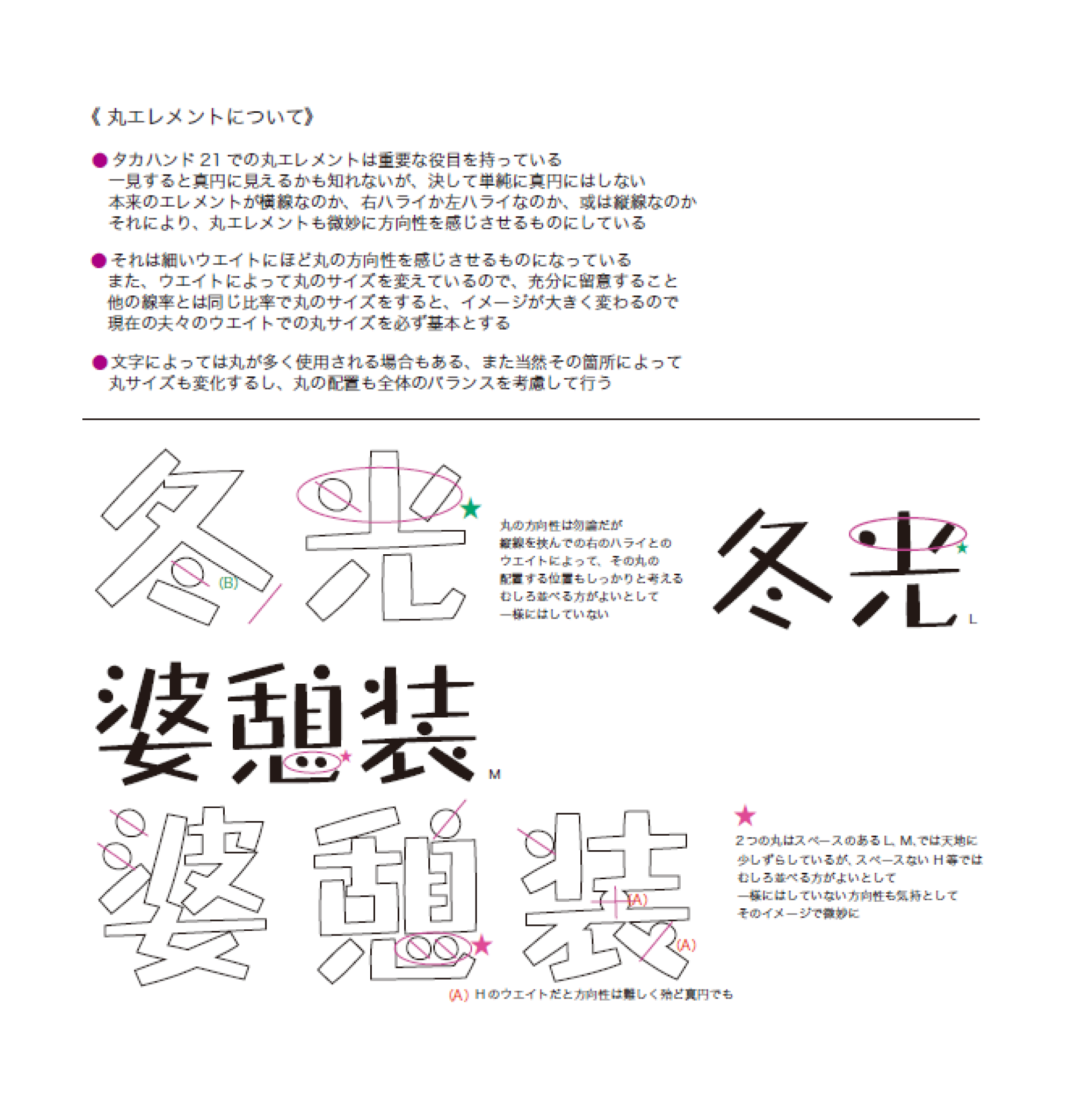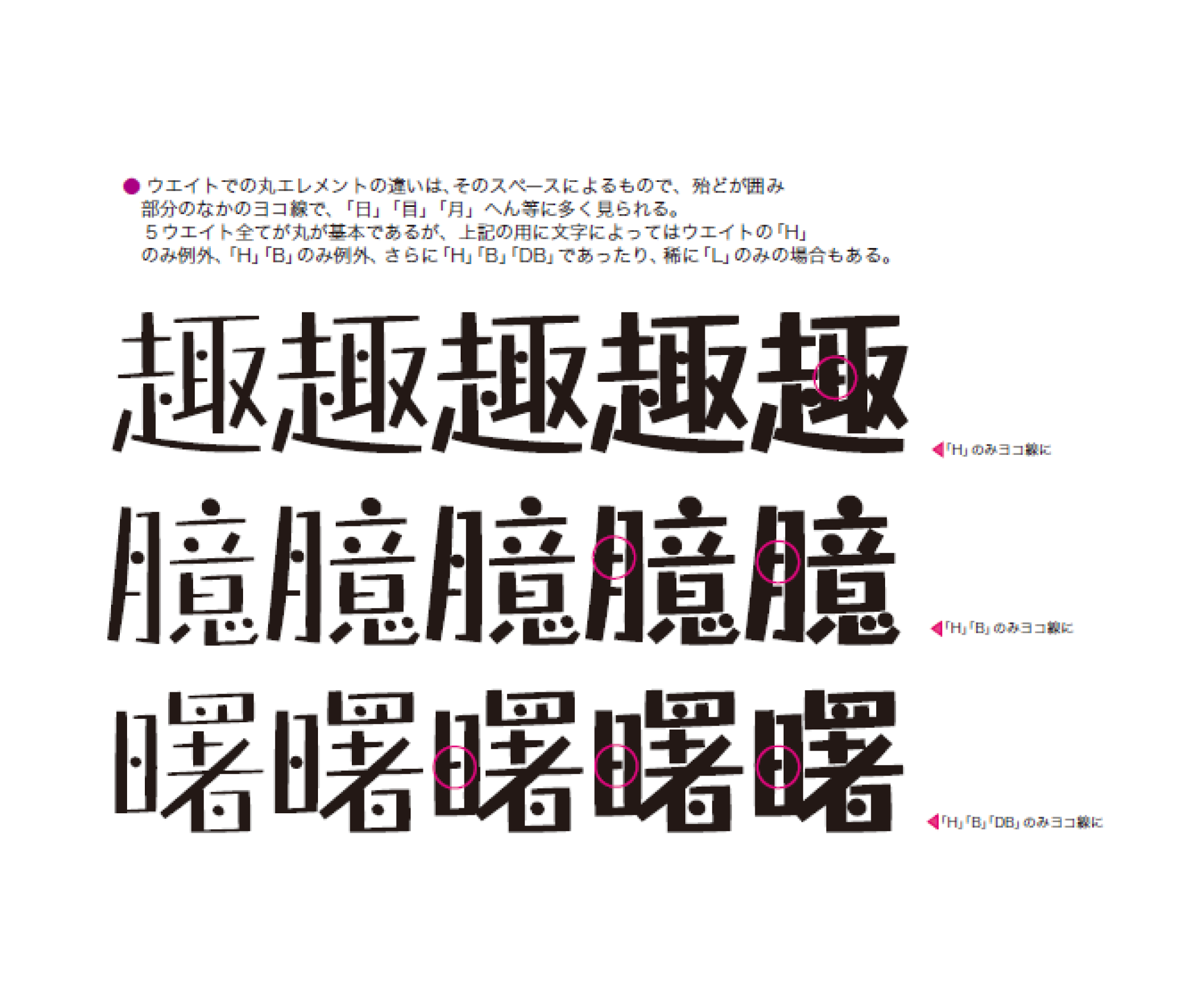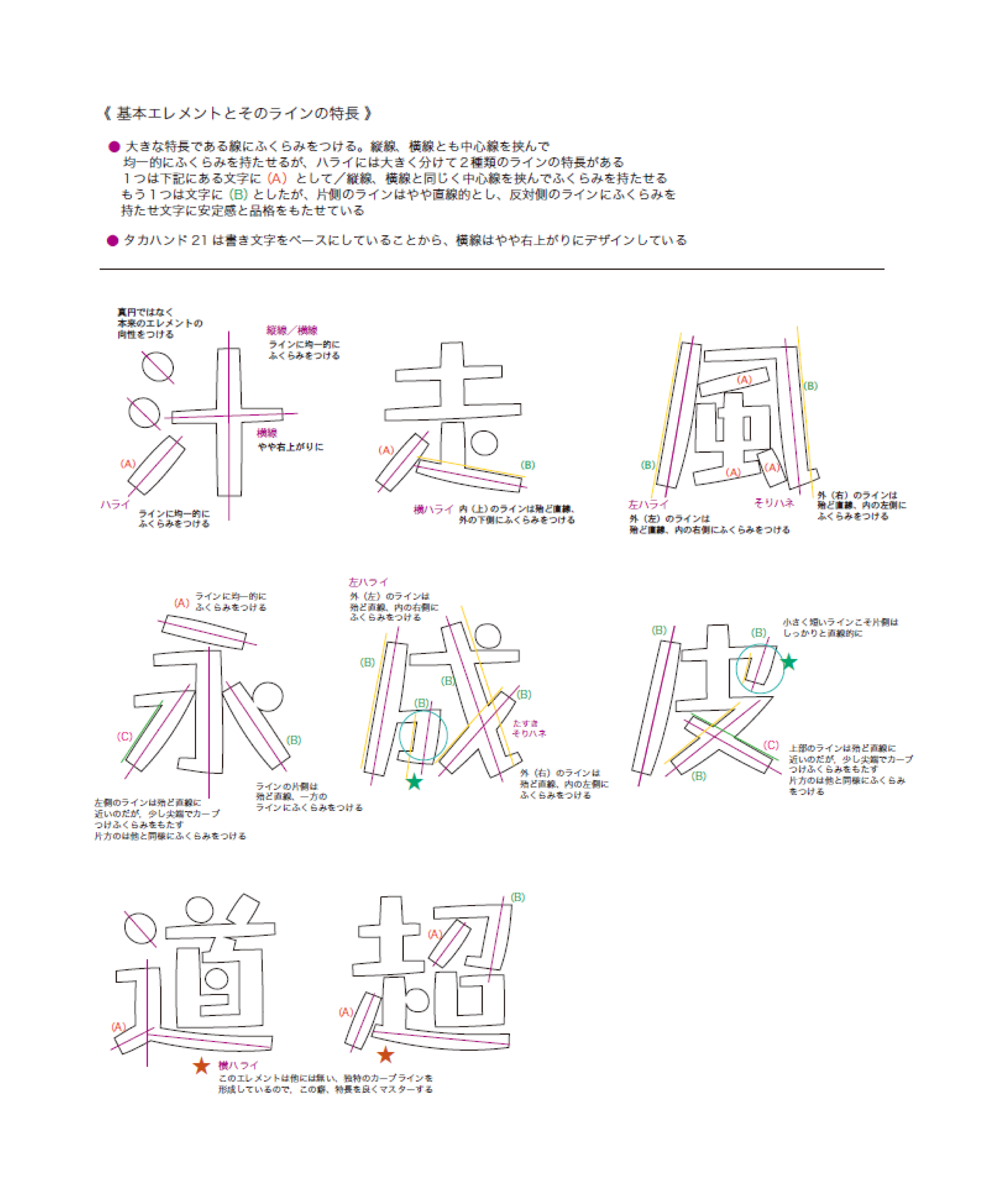
タカ書体はタイプ作家の高原新一が創作する、個性豊かな仲間たちです。どの書体も人間味に溢れ、温もりある魅力の顔をもってます。 ファミリーを基本として制作し、タカ書体の原点でもあるアナログ感覚の「手書き書体」も数多く取り揃えております。一貫した創作テーマは「手書き風の味わいと温もり」です。 代表作のひとつでもある「タカハンド」にも待望の新バージョンが誕生し、ほかにも多くの新しい顔ぶれが登場しております。
タカ書体であなたの素敵な表現の花をいっぱいに咲かせてください。